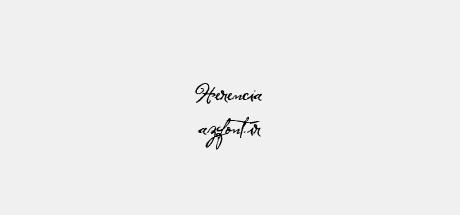
Herencia
فونت زیبای رایگان Herencia
قلم زیبای Herencia از سری قلم های بسیار زیبا برای تایپوگرافی و لوگو تایپ می باشد.این قلم در وزن Regular و توسط Linotype Design Studio and Nadine Chahine طراحی و منتشر شده است.